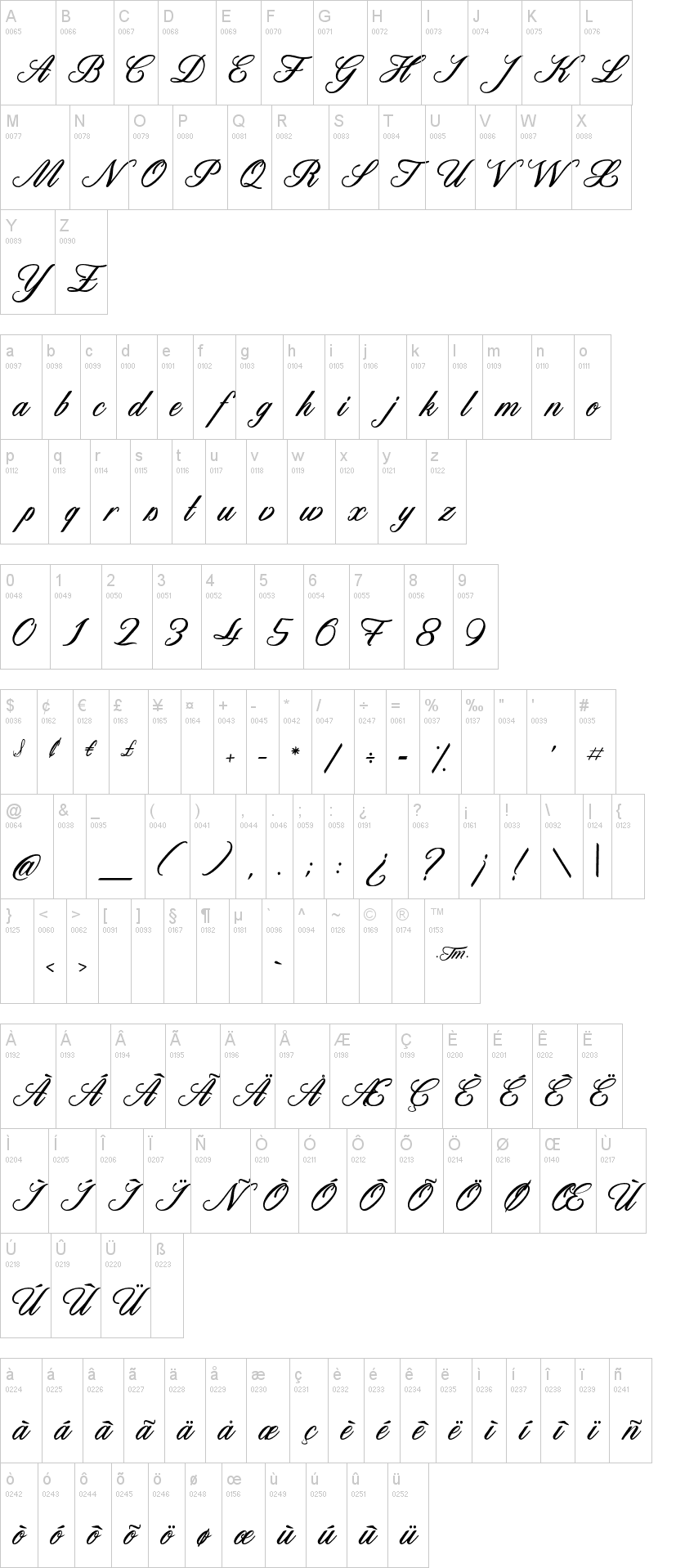
? Catherine de Beaumont是一款由著名设计师Charles Nix所设计的英文字体。这款字体具有精致、优雅的风格,更是拥有浓郁的经典气息。其字体的笔画细腻,行距舒适,同时又不失稳重,适合用于报刊杂志,书籍出版,海报等类型的文字设计。内容介绍
Catherine de Beaumont是一款非常不错的手写艺术字体,具有很好的视觉感,适合于文化类的宣传设计、商业类品牌的广告和产品包装设计以及个性化文字排版等较多场景。